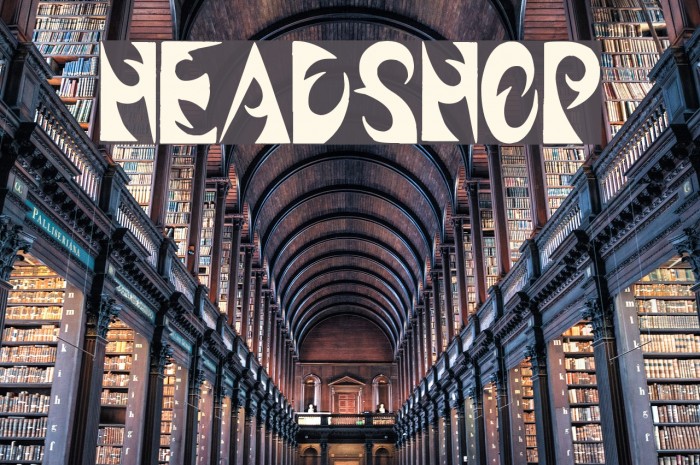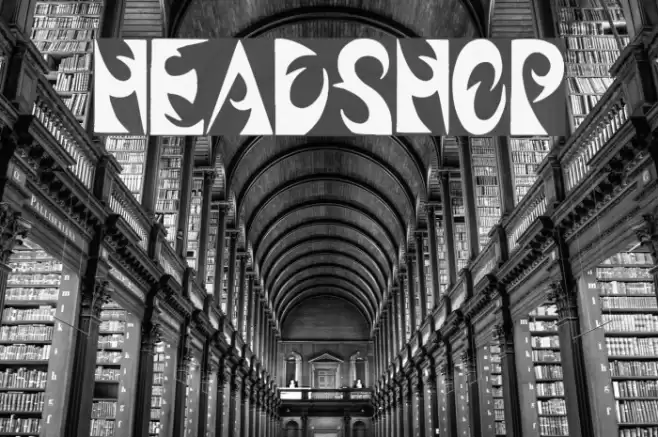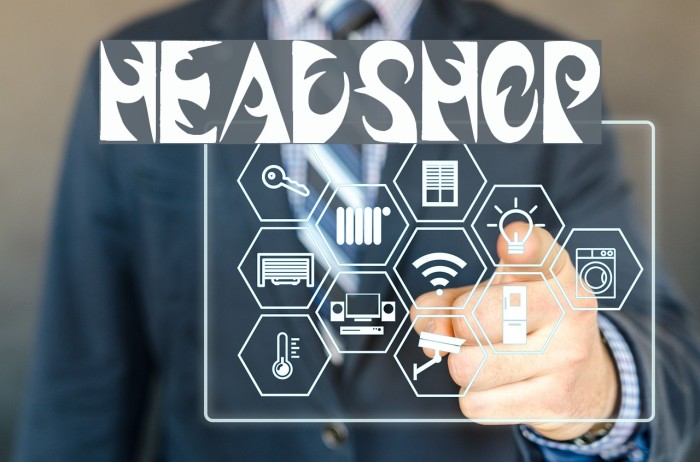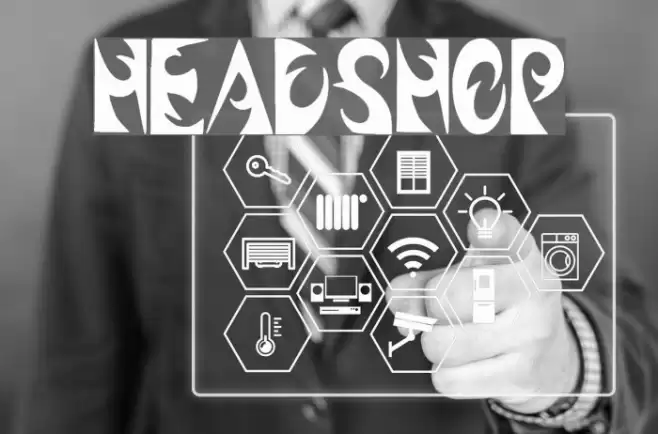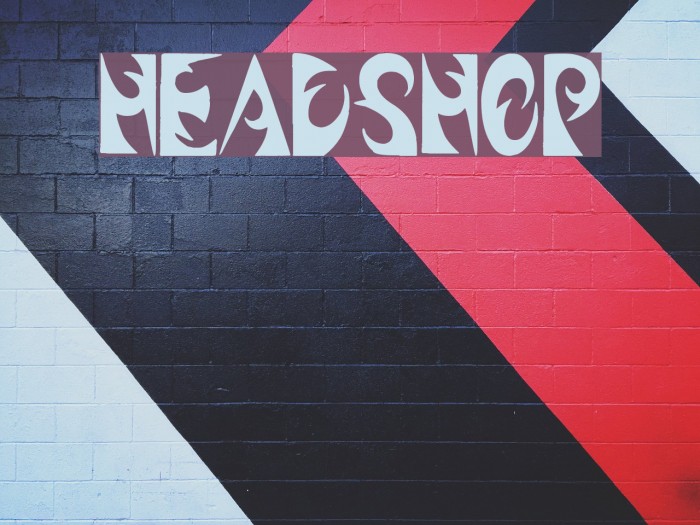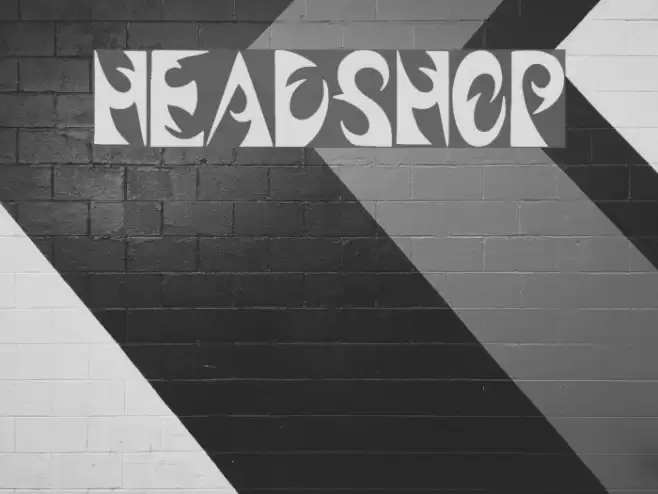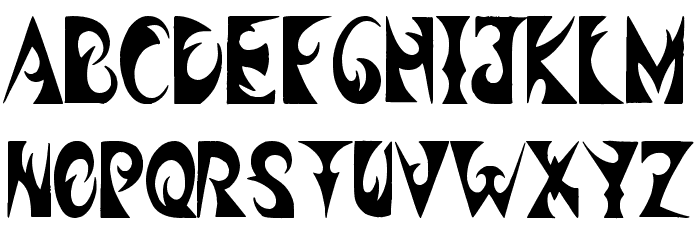
Headshop Font
| Категория | Curly |
| Рекомендуемые проекты | This font is perfect for album covers, posters, branding for edgy or alternative products, and any design project that requires a bold, eye-catching typeface. |